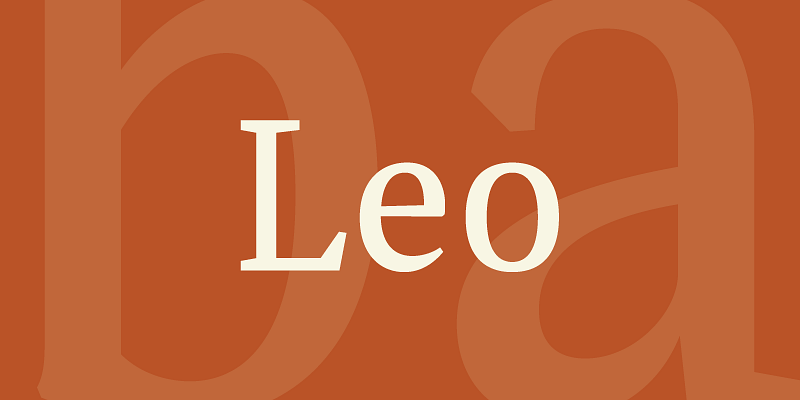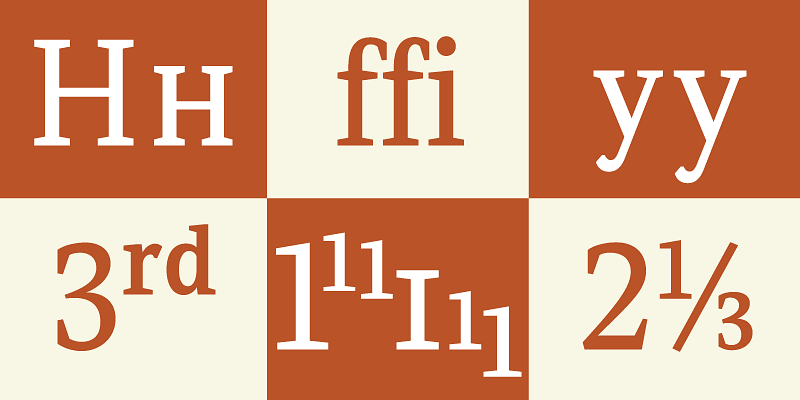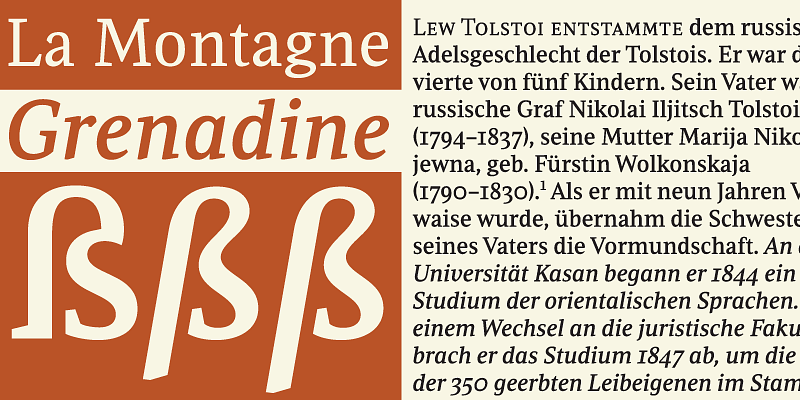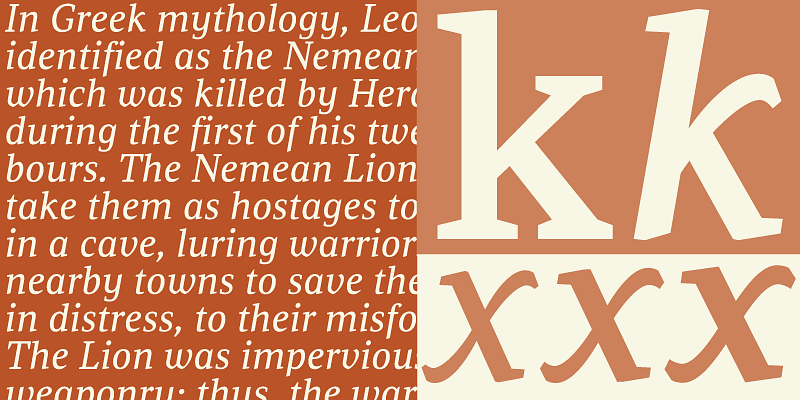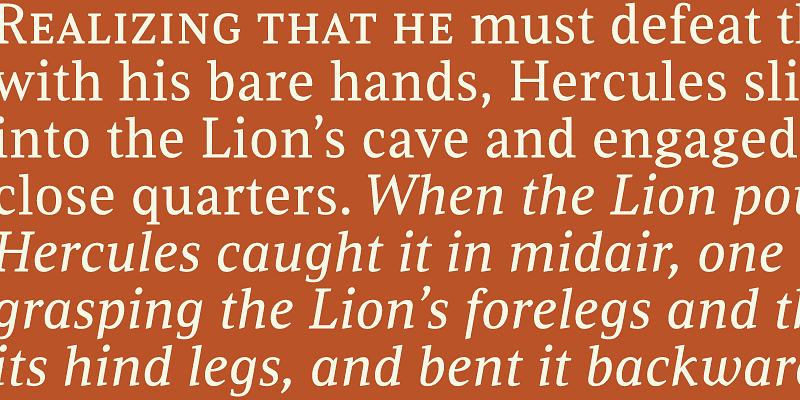
Leo est un magazine économique et un livre destiné à être utilisé dans des formats adaptés à une lecture immersive, avec différentes coupes optimisées pour différentes tailles de corps de texte, comme les notes de bas de page et le texte juridique. Son mantra est « la grâce par l’austérité ».